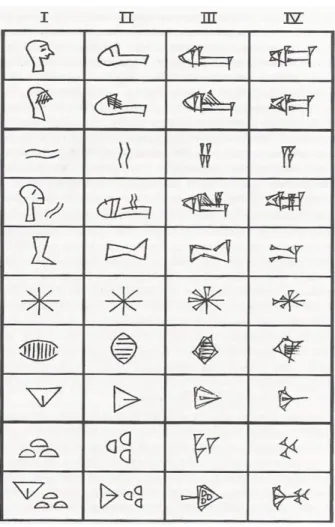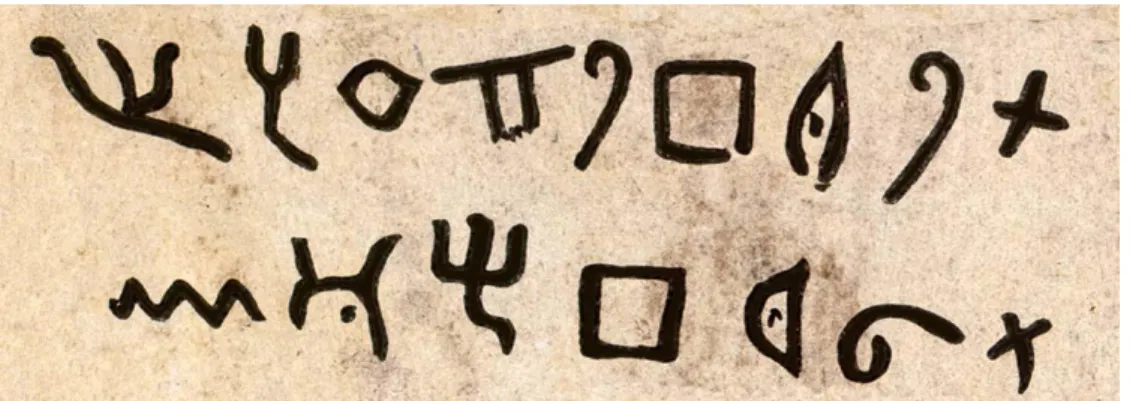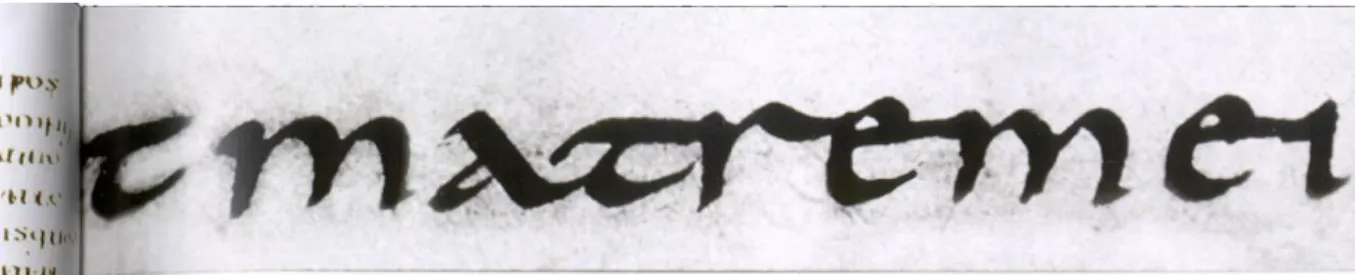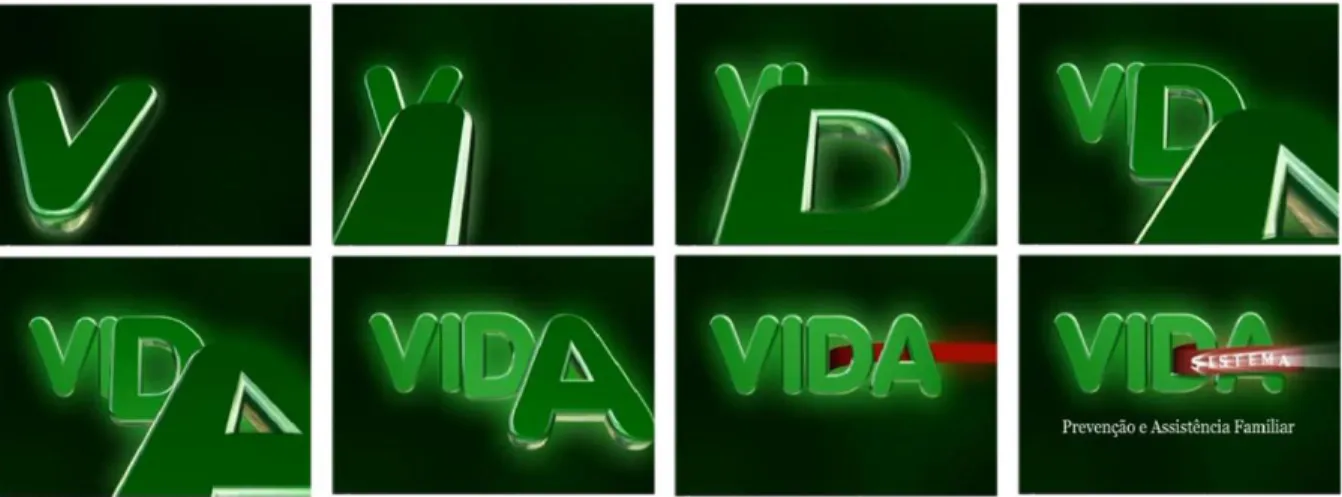
INTRODUÇÃO
Agora como tema de dissertação de mestrado, a pesquisa em escrita concentra-se no momento em que o tipo gráfico migra de uma forma bruta, física e tangível para uma tecnologia inovadora que envolve código binário, cujo efeito colateral é a adoção de uma nova linguagem usada por jovens em todo o mundo. O objetivo desta pesquisa é, portanto, estudar o momento em que o tipo 1 atinge a virtualidade, ou seja, a transição do tipo móvel dos gráficos de Gutenberg para o tipo digital das telas quando estas migram de uma estrutura física - estado que permaneceu por mais de 500 anos. anos - a ser representado por uma sequência matemática: o código binário, baseado na teoria da informação, que gerou a compressão de dados criada por Claude Shannon na década de 30 do século XX - a linguagem do computador - arcabouço de todos os softwares.
DO PICTOGRAMA À ESCRITA MECANIZADA
A pictografia é, portanto, a primeira manifestação da escrita, caracterizada pela representação de um desenho aliado ao seu significado. Surge, portanto, a necessidade de um código que estabeleça o controle sobre as ações do homem e essas ações, que antes eram relegadas ao esquecimento, agora têm uma forma de perpetuação na escrita.
A escrita hieroglífica
O conceito de escrita espalhou-se como um vírus, a ideia de escrever espalhou-se da Mesopotâmia ao Nilo. Os escribas incorporaram muitos elementos da escrita hieroglífica na escrita hierática e esses elementos foram abstraídos até não terem mais qualquer ligação com sua origem.
A escrita chinesa
A escrita suméria
O surgimento da escrita provocou uma grande transformação na memória coletiva dessas pessoas, antes relegadas à oralidade. Quase ao mesmo tempo, diversas pessoas em diferentes regiões do mundo perceberam a necessidade de escrever como um disco.
A escrita proto-canaanita
O alfabeto fenício
A melhor forma de entender essa situação é traçar um paralelo com a escrita fonética atual, que pode representar com precisão qualquer som em qualquer idioma, utilizando caracteres específicos daquele tipo de escrita ou alfabeto. O desenvolvimento do alfabeto significou uma transição de um mundo onde a comunicação era predominantemente oral para um mundo visual.
O alfabeto
Bustrophedon” (o caminho do boi) uma linha consecutiva da esquerda para a direita e a seguinte da direita para a esquerda. O ato de ler envolvia ler em voz alta para que as pessoas ao redor pudessem perceber a fronteira entre as palavras.
O alfabeto etrusco
Outro fato importante a ser observado é a postura e os maneirismos do escritor na utilização desses novos suportes, além dos novos instrumentos que deram origem a letras mais refinadas. Na era digital, o destinatário é também o remetente; ele também está sozinho, mas seu poder de interação é grande.
Alfabeto romano
O romano também introduziu a técnica de escrita com caneta e tinta (em pergaminho), que resultava em traços finos ascendentes e grossos descendentes. Este tipo de fonte favorece o aparecimento de uma certa irregularidade com letras maiores que outras. Mais uma vez, o tipo de escrita ou a forma de escrever começa a impor uma autonomia que sabemos hoje ter sobrevivido ao longo dos tempos.
A escrita protegida
Como você pode ver, na frase EGOSVMLVXMVNDI, algumas letras podem ser interpretadas como números, o contexto mostrará se são letras ou números.
A escrita uncial
Somente no século XV essas letras que serviam como algarismos romanos foram substituídas por algarismos arábicos. Um dos mais belos exemplos desta carta está no Livro de Kells, escrito por monges irlandeses no século VIII.
A minúscula carolíngia
A letra humanista
A letra gótica
No século XII, a vida cultural na Europa deslocou-se dos mosteiros para as recém-criadas universidades de Paris, Montpellier, Oxford, Cambridge, Bolonha e outras cidades, formando um número considerável de intelectuais. Na verdade, este era um processo adormecido, uma vez que os romanos, já no século III, utilizavam um processo de impressão semelhante à xilogravura. Os egípcios também imprimiram desenhos em tecidos, e os japoneses fizeram suas primeiras impressões já no século V.
DOS TIPOLOGISTAS AO CYBER- HIEROGLIFO
A gráfica de Gutenberg (da letra ao tipo)
Pode-se deduzir, portanto, que a chegada da imprensa, associada à sua rapidez de produção, foi uma das responsáveis pela cisão da Igreja Católica no século XVI. A prática de debater era comum entre os professores de teologia, como exercício de discussão de assuntos como indulgências, sendo o local habitual a porta da igreja. Embora sem a intenção de criar briga, a invenção da imprensa causou tal situação, pois se sabe que Gutenberg tinha uma finalidade comercial para a impressão, que era copiar livros mais rápido que os copistas e, portanto, mais barato.
Os tipologistas
Sua conquista foi ter criado um tipo de letra adaptado às necessidades de impressão no início do Renascimento. É nos livros impressos por Manutius que se registra a primeira aparição da letra itálica, criada por seu sócio Francesco Griffo, fonte com ligeira inclinação para a direita (apenas as letras minúsculas). No final do século XVII, Phillipe de Grandjean, diretor da Louis
CONSIDERAÇÕES FINAIS
Todas essas mudanças são resultado de uma situação que altera o meio escrito e, consequentemente, a forma de escrever. Um factor óbvio, claro, é a necessidade de uma língua comum ou língua franca – um conceito tão antigo como a própria língua. O Unicode parece ser o sistema mais próximo de apoiar a ideia de uma escrita universal, em vez de uma linguagem no sentido mais amplo.